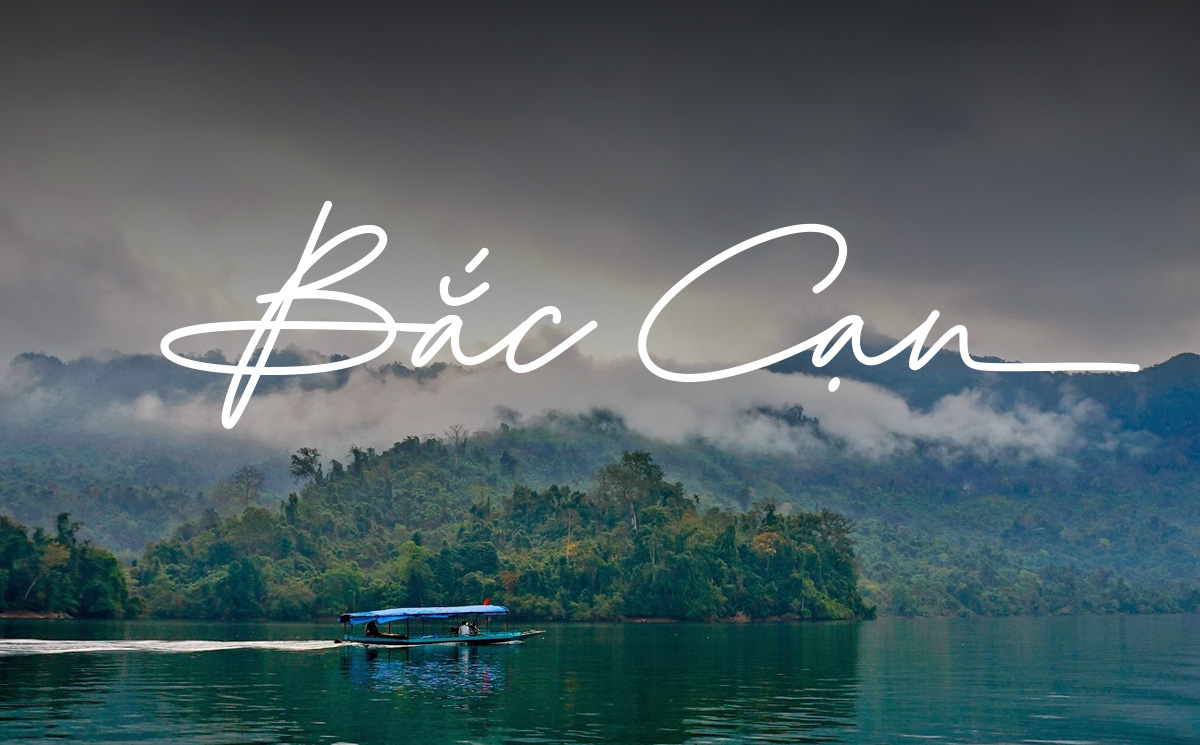
Font Chữ Ký TH The Billion Việt Hóa
Giới thiệu Font Chữ Ký TH The Billion Việt Hóa
Nếu bạn đang tìm kiếm một phông chữ mang đậm dấu ấn cá nhân, thanh lịch và bay bổng, thì TH The Billion chính là sự lựa chọn hoàn hảo. Đây là một font chữ ký (signature font) được thiết kế với những đường nét mềm mại, tự nhiên như chữ viết tay thật, giúp tác phẩm của bạn toát lên vẻ sang trọng, tinh tế và đầy nghệ thuật.
Bản việt hóa của TH The Billion đã được tinh chỉnh kỹ lưỡng, đảm bảo các dấu câu tiếng Việt hiển thị đẹp mắt, mượt mà và không bị lỗi phông hay gãy nét khi thiết kế.
Đặc điểm nổi bật của TH The Billion
• Đường nét uyển chuyển: Các nét thanh đậm được chuyển đổi tự nhiên, tạo cảm giác chân thực như một chữ ký được viết bằng bút mực.
• Việt hóa chuẩn xác: Dấu tiếng Việt được chăm chút tỉ mỉ, dấu câu đặt đúng vị trí, kerning (khoảng cách giữa các ký tự) hợp lý giúp tổng thể chữ hài hòa.
• Ký tự thay thế (Alternates) phong phú: Hỗ trợ các nét swash nối đuôi dài ấn tượng, giúp bạn dễ dàng tạo ra những cụm từ có độ luyến láy độc đáo.
Ứng dụng hoàn hảo cho mọi dự án
Với sự linh hoạt và thanh lịch, font chữ ký TH The Billion Việt hóa là “vũ khí” đắc lực cho các thiết kế:
• Thiết kế Logo & Branding: Tạo ra những logo cá nhân, thương hiệu thời trang, spa, mỹ phẩm mang đậm tính độc bản và cao cấp.
• Thiệp cưới & Sự kiện: Mang lại sự lãng mạn, bay bổng cho thiệp mời, phông nền tiệc cưới hay photobooth.
• Bao bì sản phẩm (Packaging): Tôn lên vẻ sang trọng cho nhãn mác, vỏ hộp sản phẩm.
• Nhiếp ảnh & Social Media: Làm watermark chữ ký cho nhiếp ảnh gia, tạo điểm nhấn cho các trích dẫn (quotes), lookbook, hay bài đăng mạng xã hội.